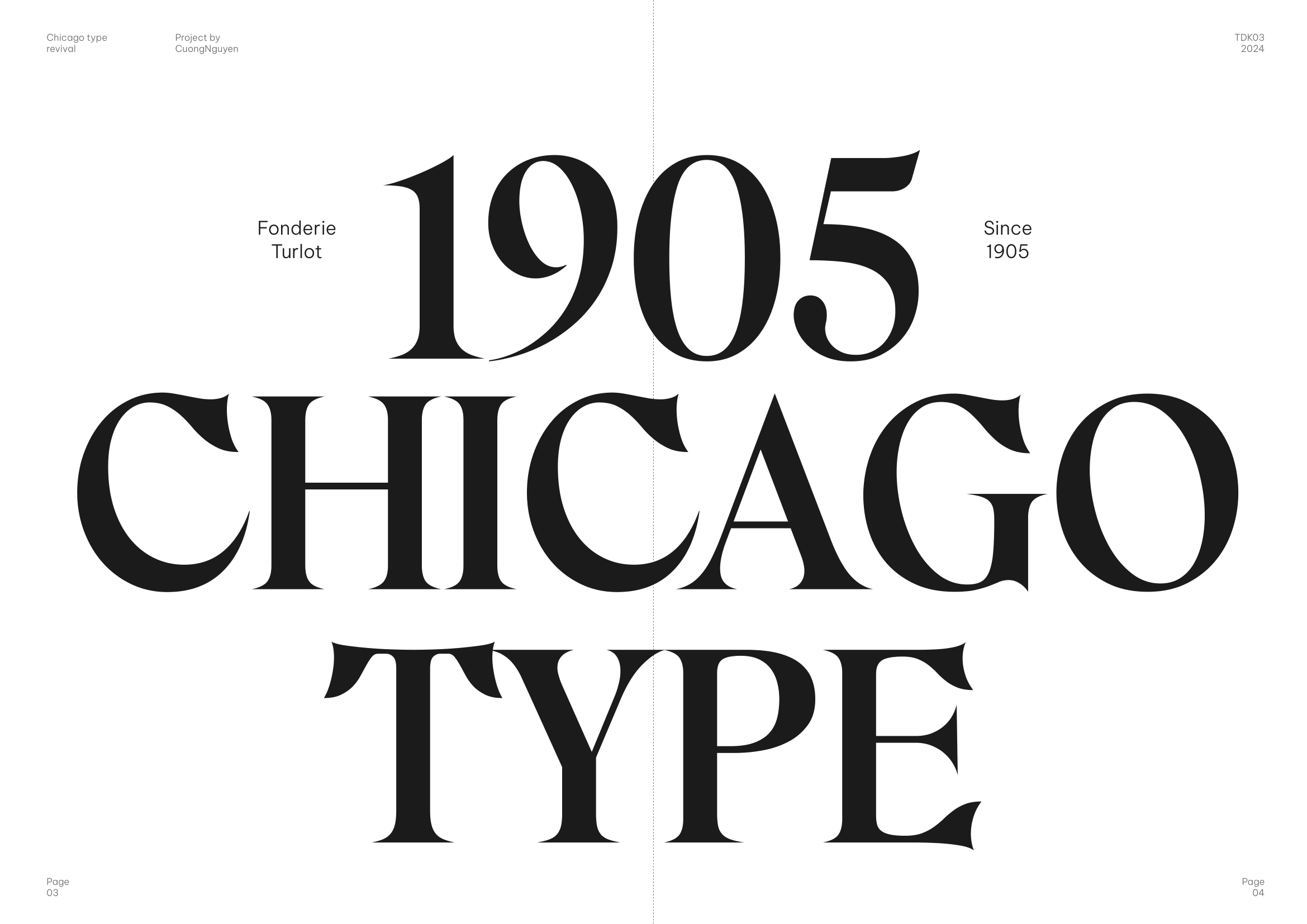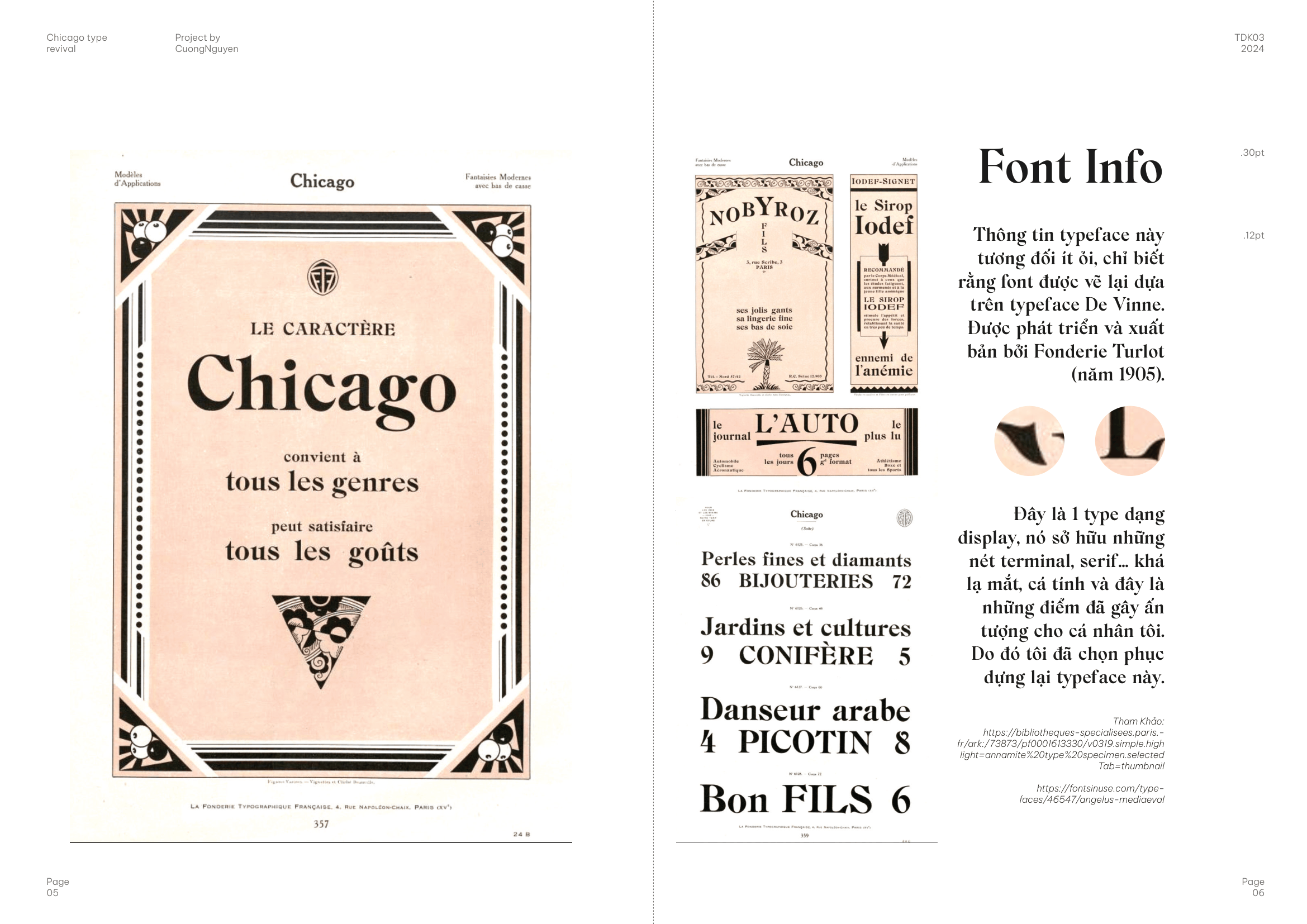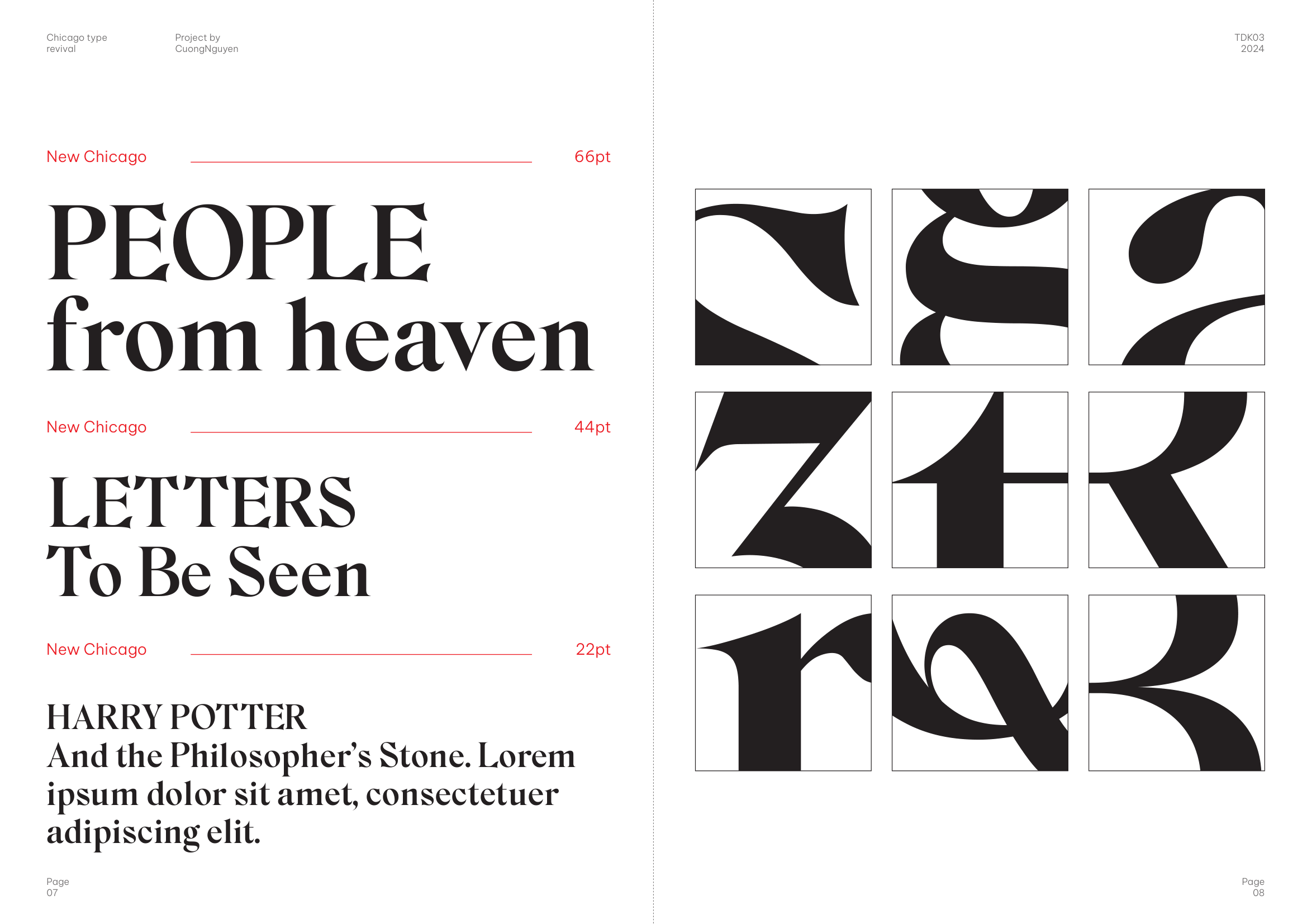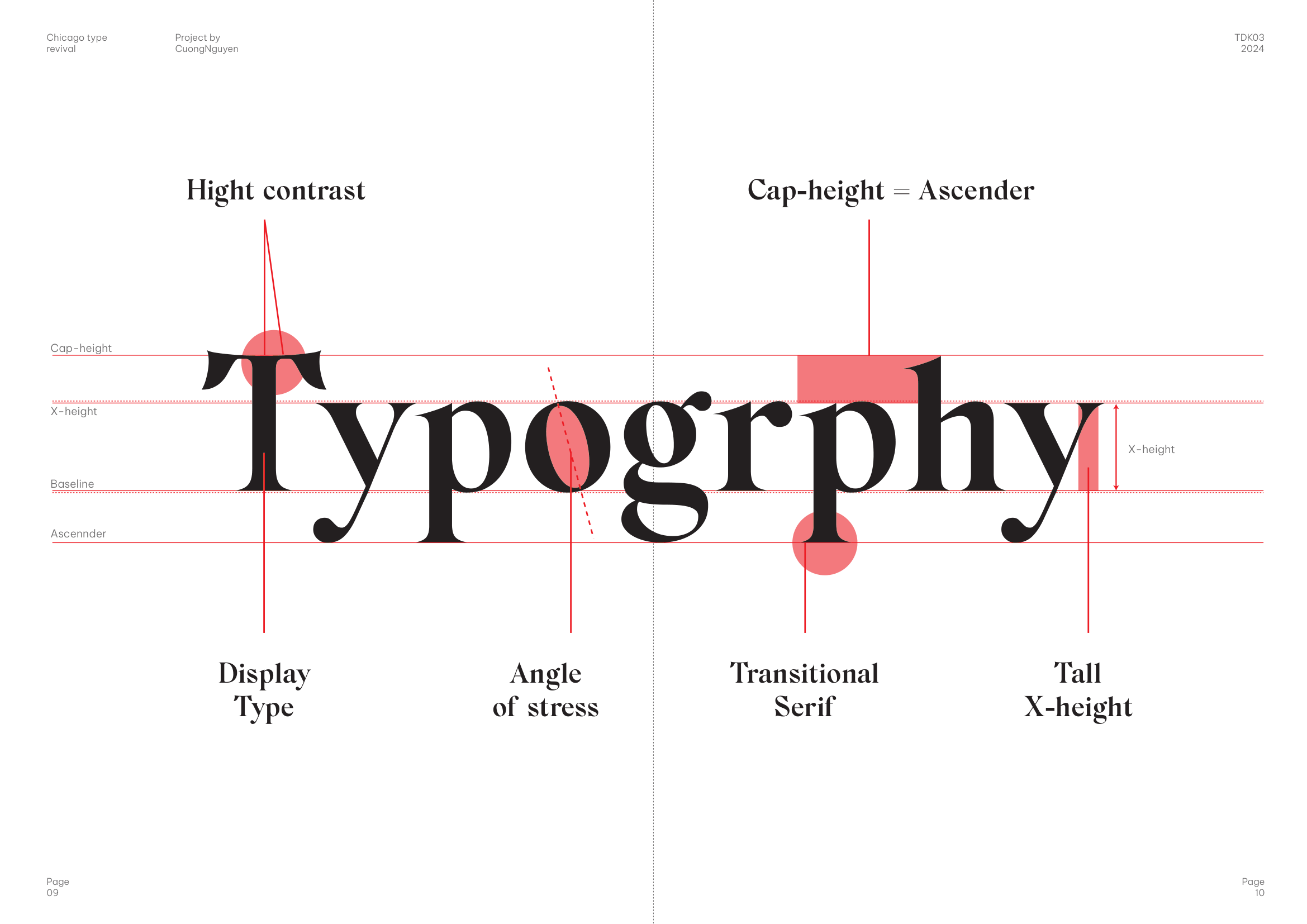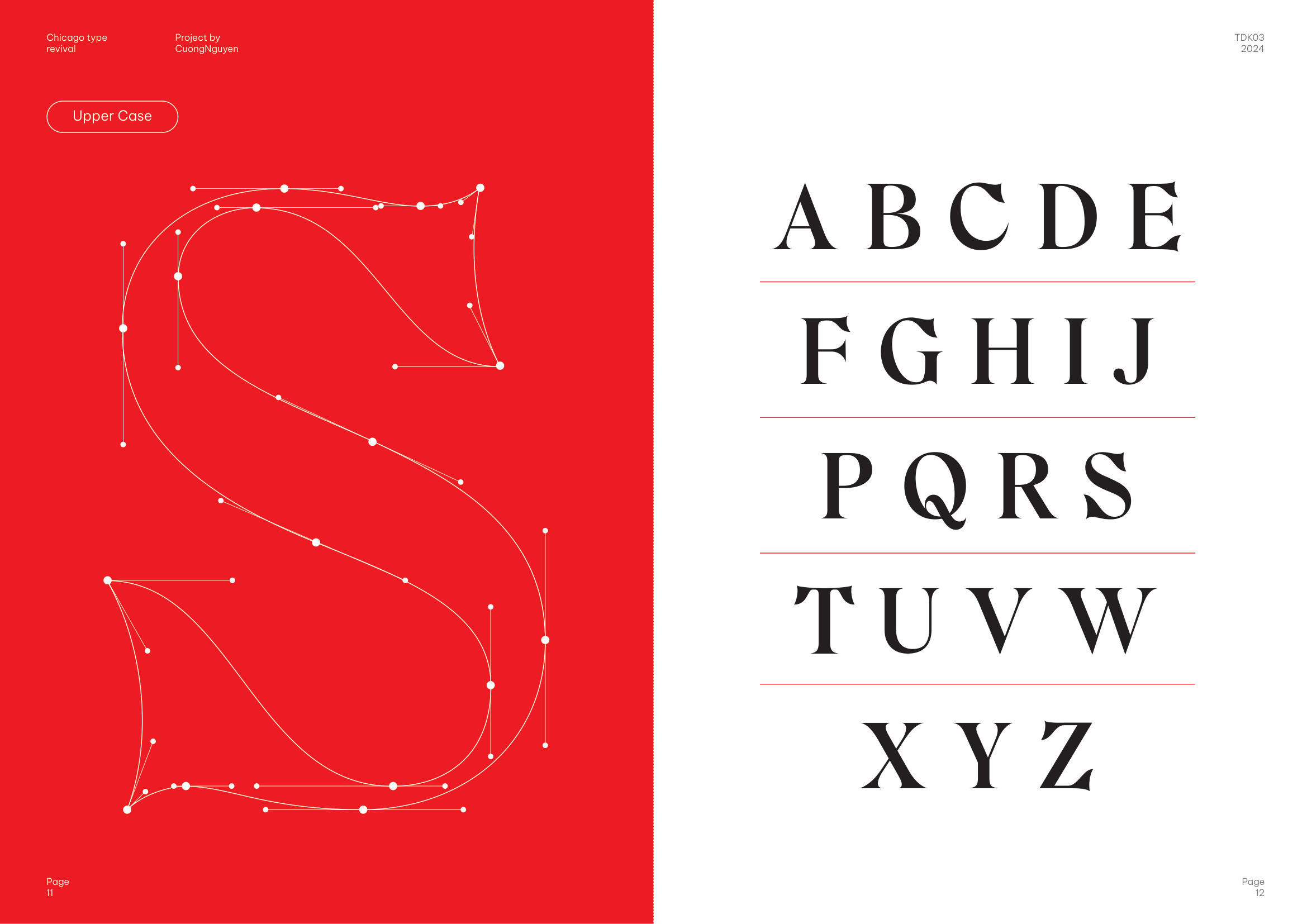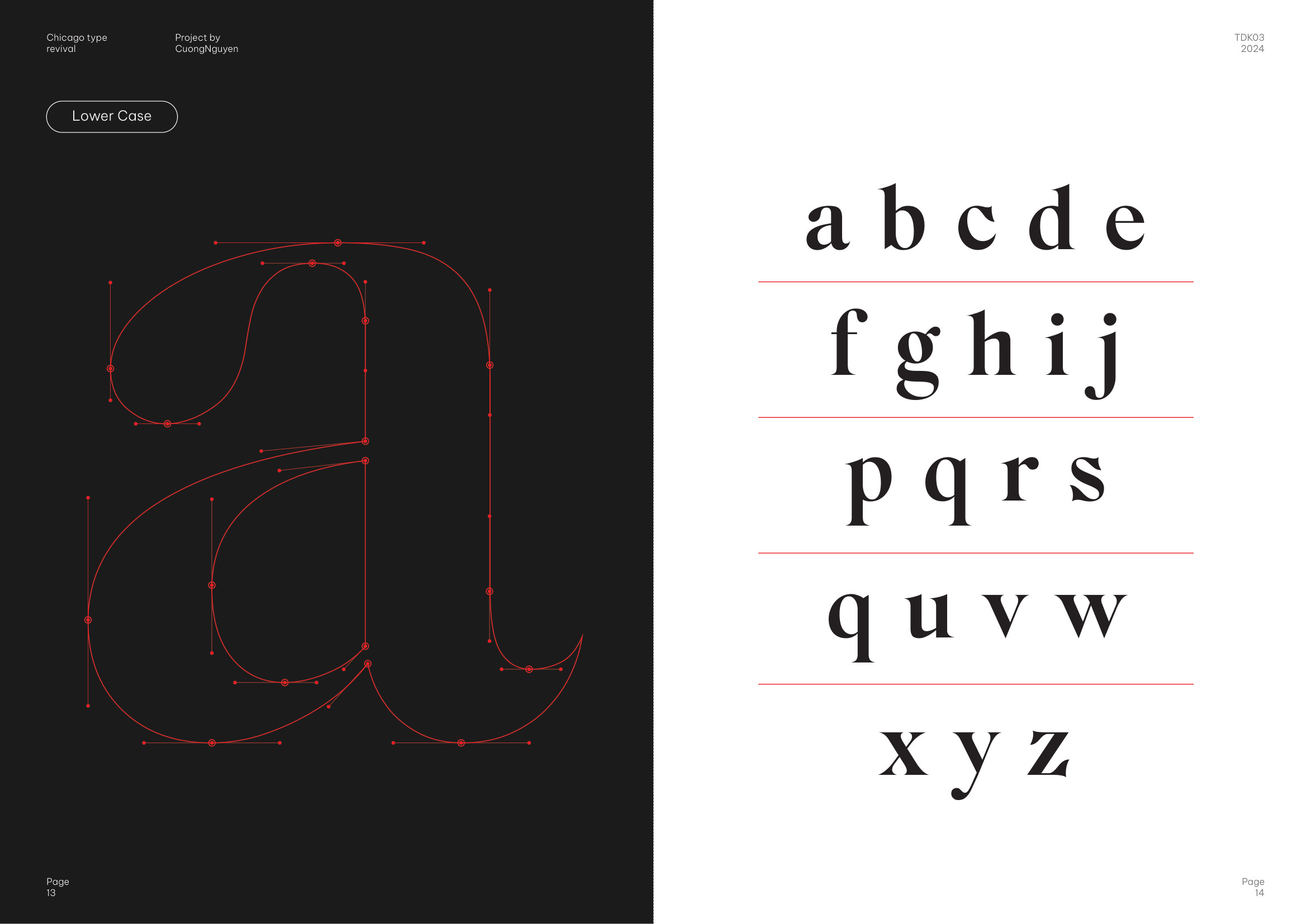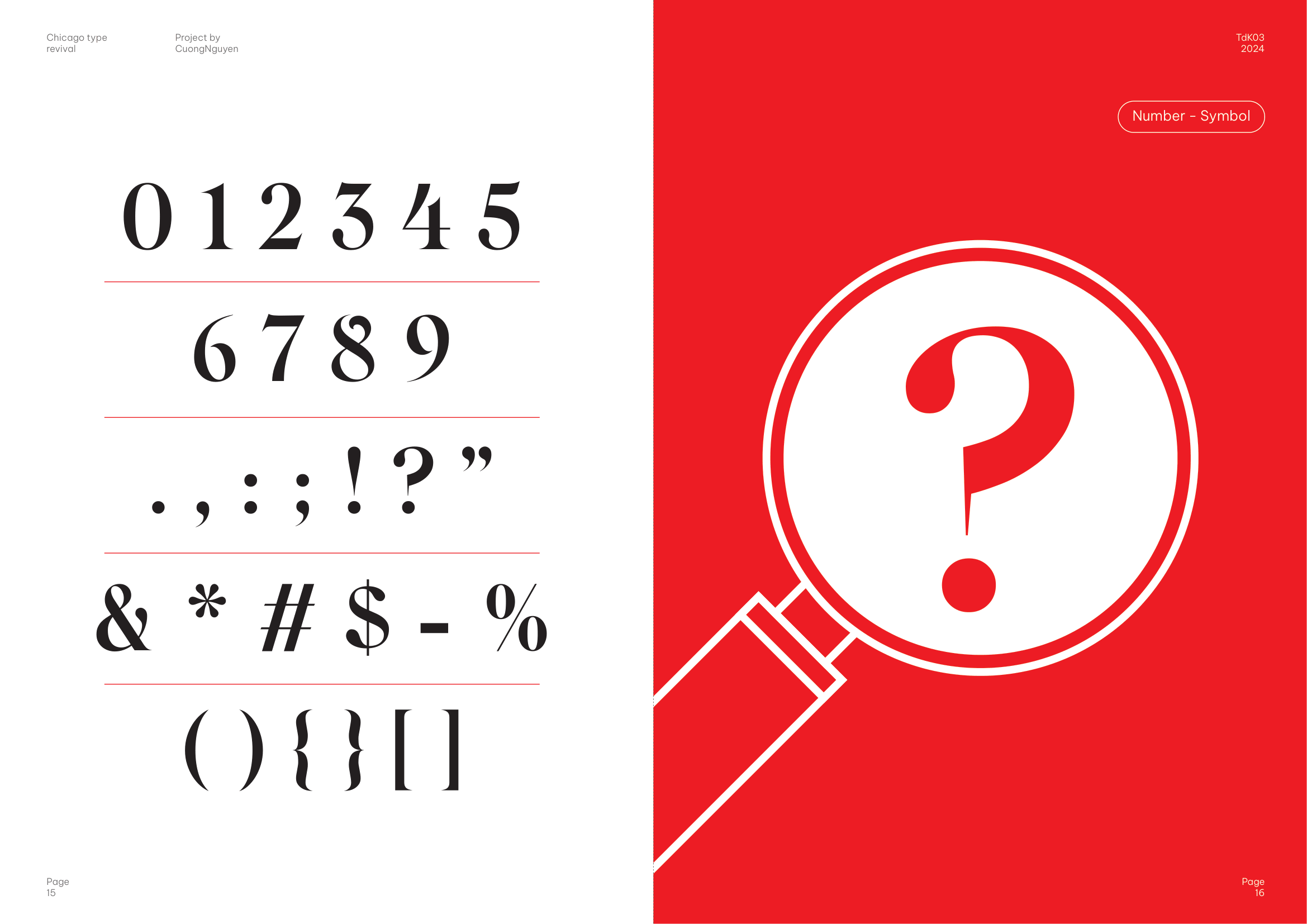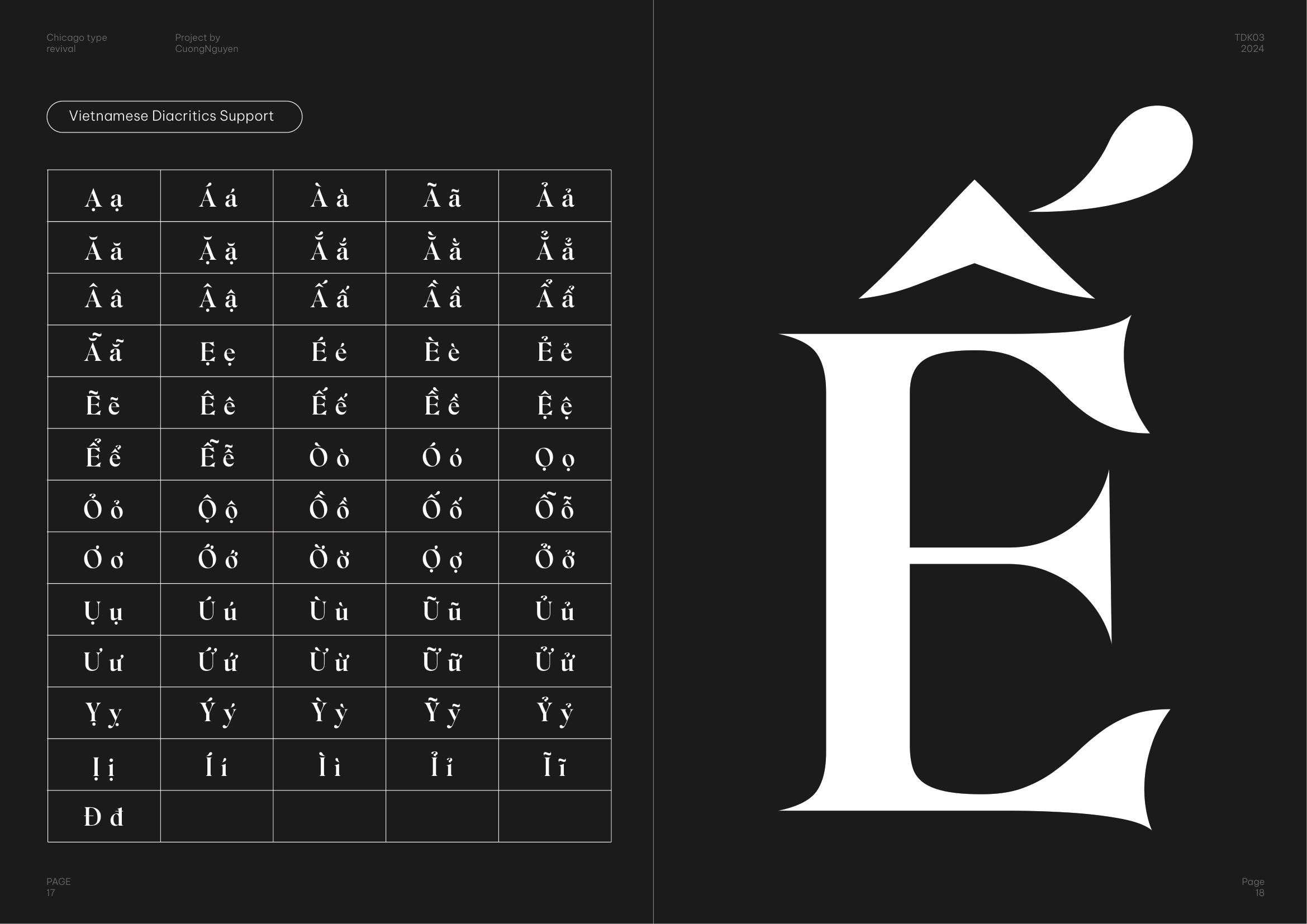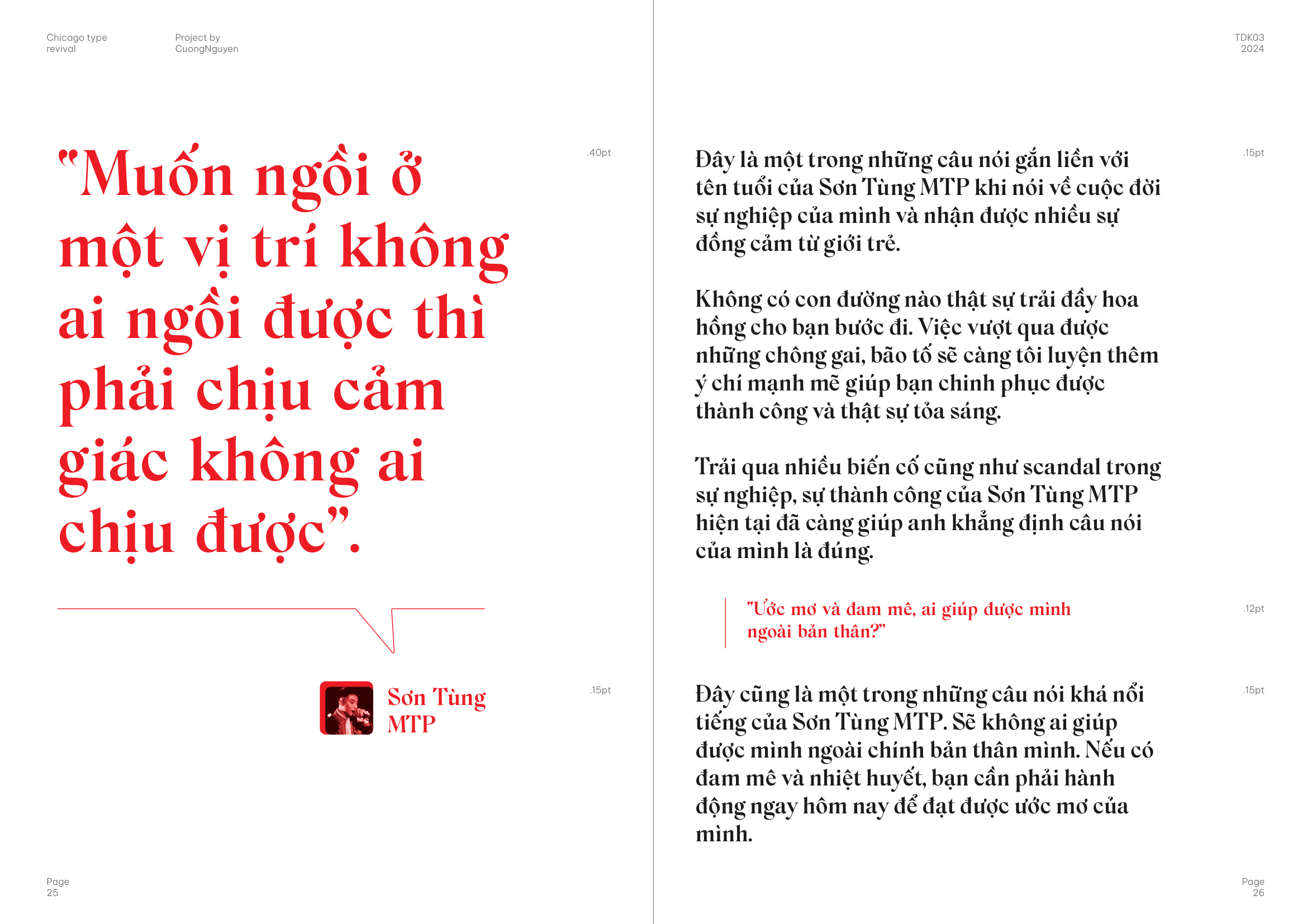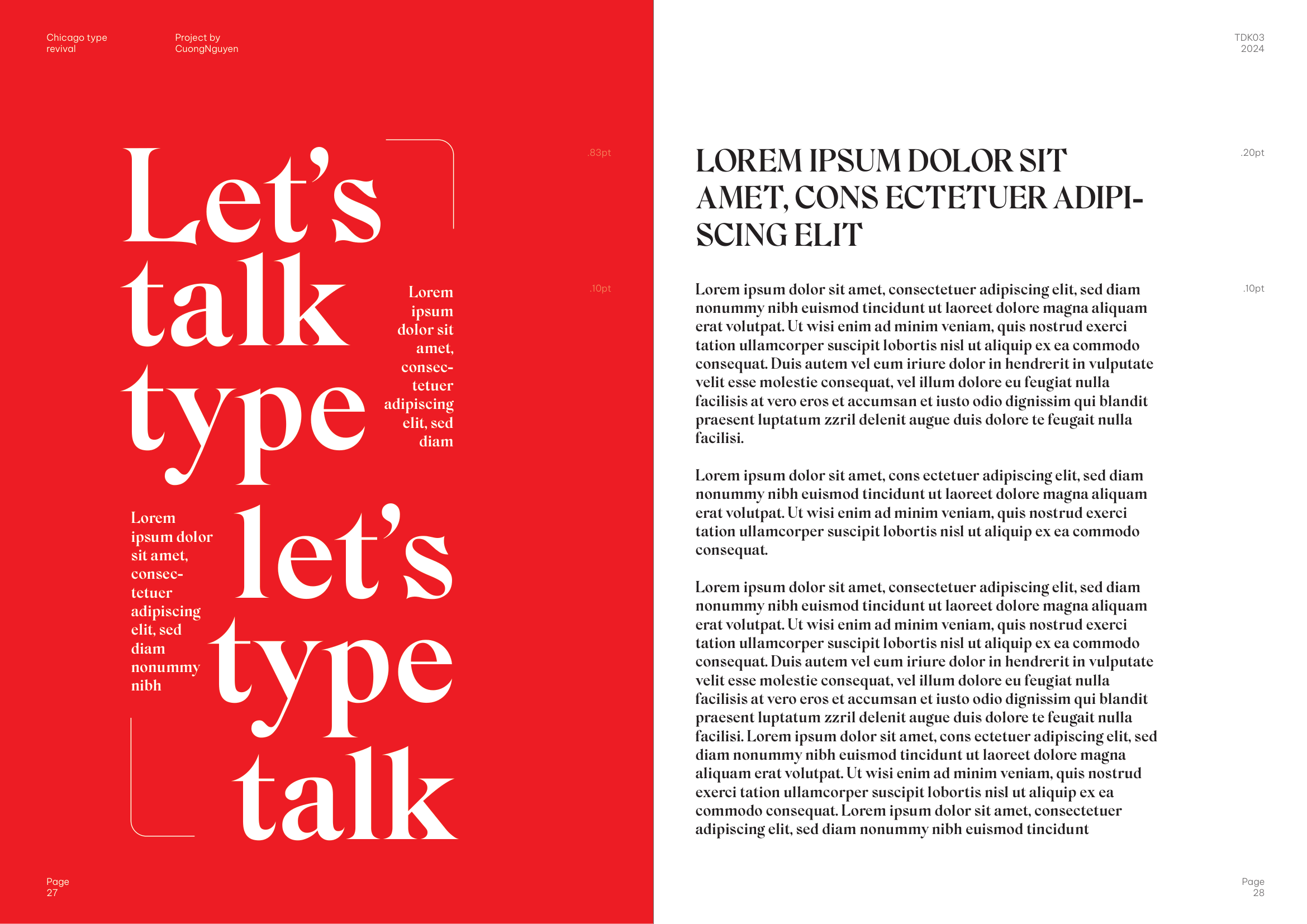
Chicago
Về Chicago: Chicago cường điệu những nét vuốt cong sắc lẹm. Dáng tròn gợi mở mà nét đâm nhọn hoắt khác nào nói có rồi lại làm thinh. Những trái chiều lúc nào cũng hết mực kịch tính.
Transitional Serif
Display
Naming a bold display face after an American city, Chicago, was very much in the spirit of the era.
The late 19th and early 20th century was a period of great fascination in Europe with American industrial modernity, and French foundries often gave their display and poster types names that evoked energy, scale, and the exotic. Chicago, as one of the fastest-growing cities in the world at the time, fit perfectly as a name for a powerful, assertive display face. The Turlot foundry's catalog from this period was focused heavily on caractères d'affiches, large, bold poster typefaces, reflecting the boom in commercial printing and advertising at the turn of the century.